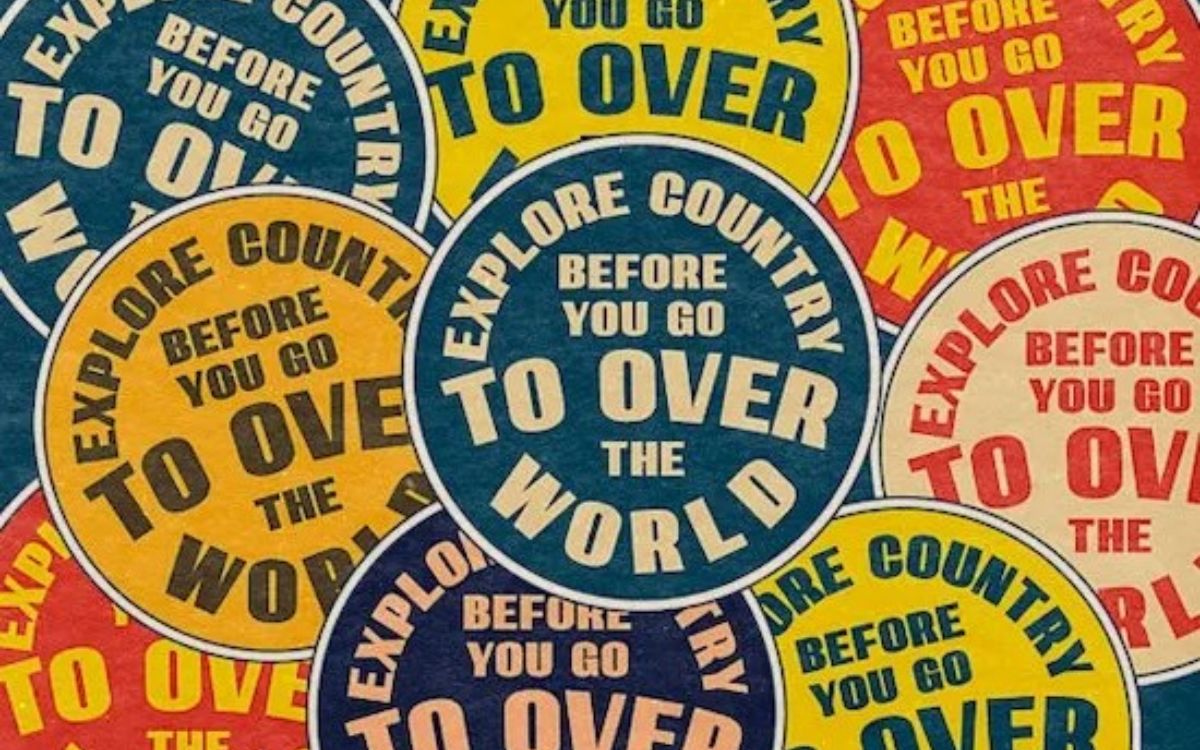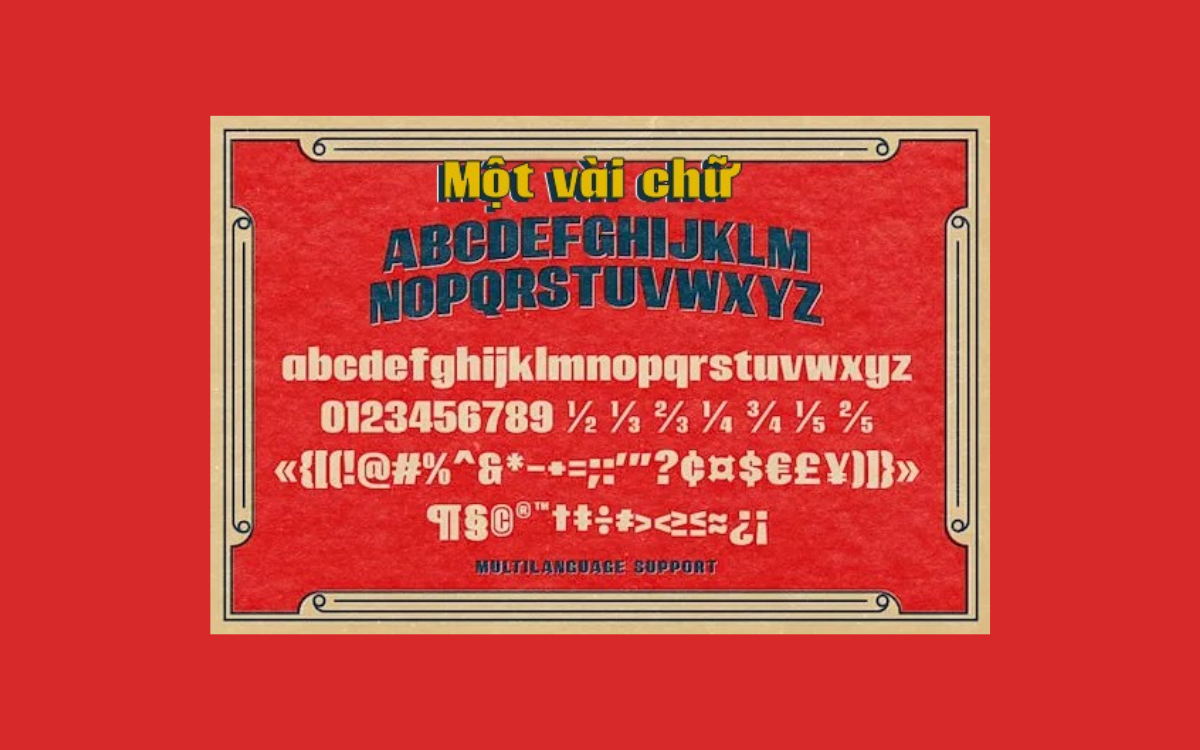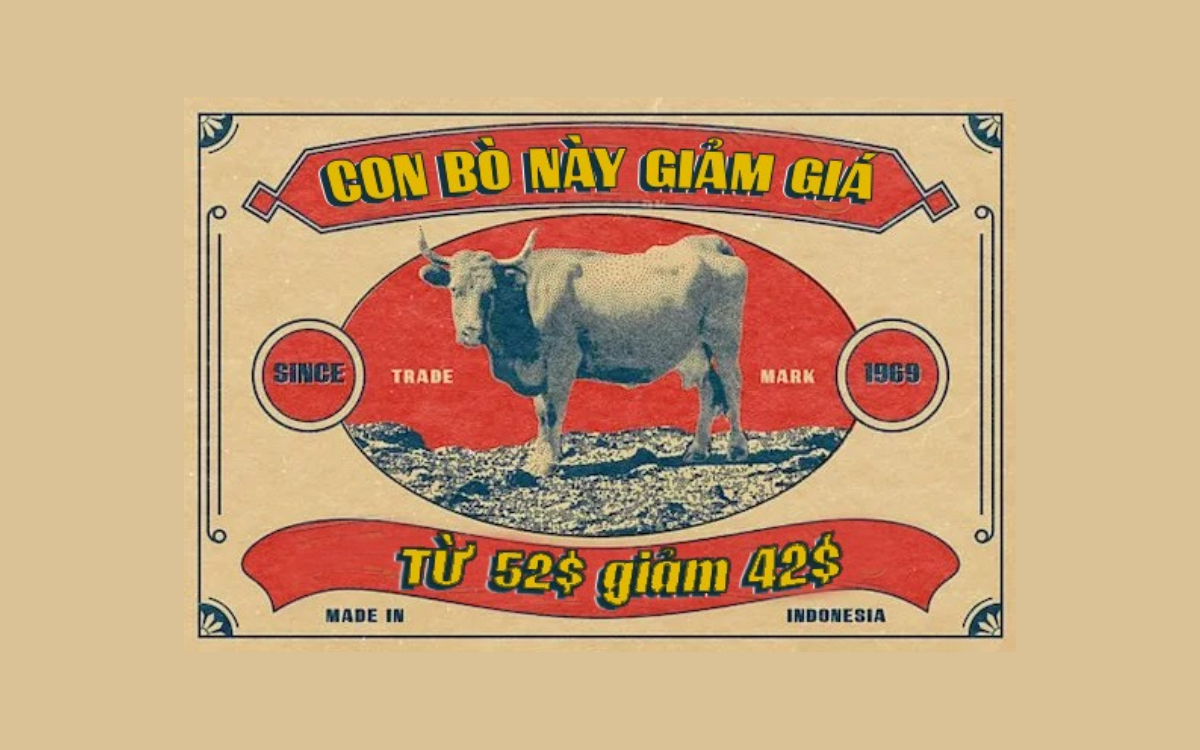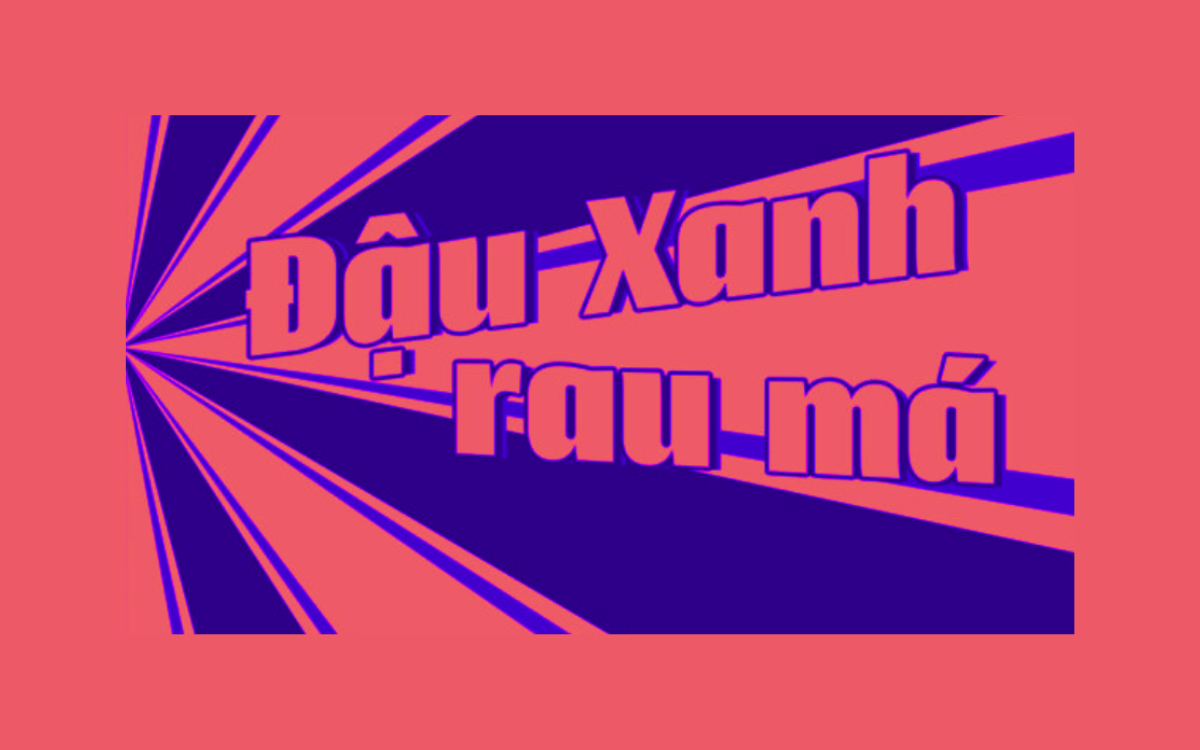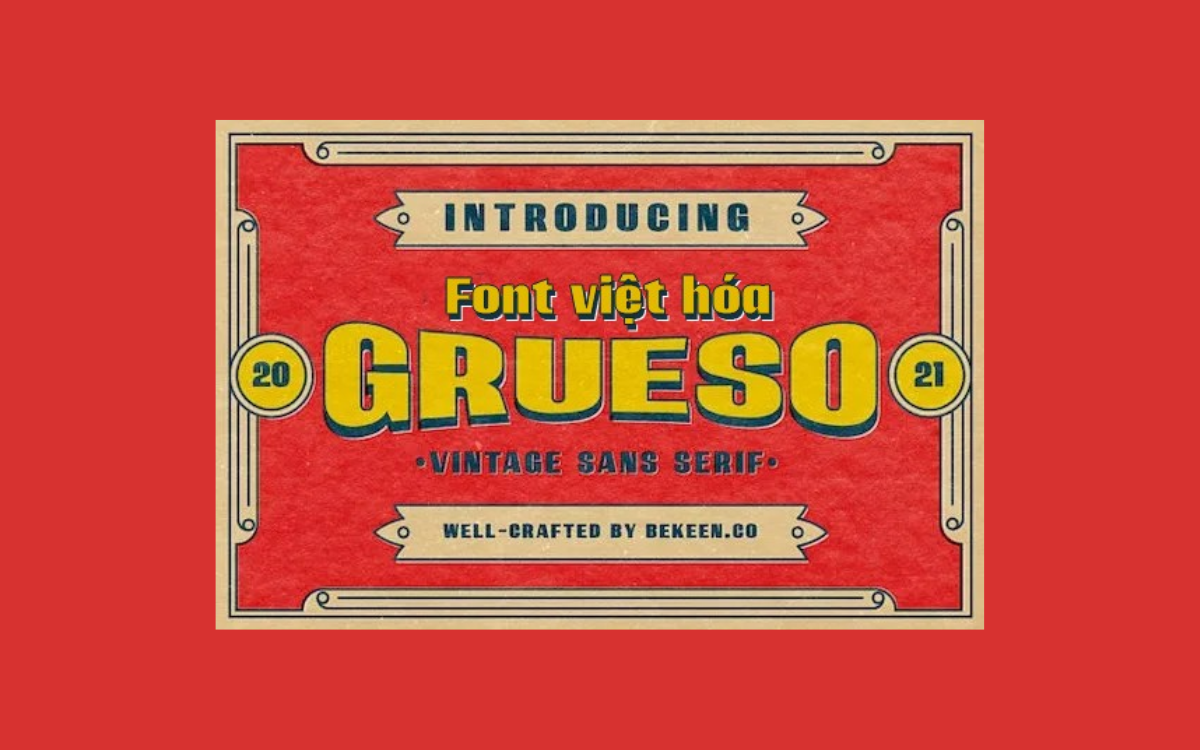
Font MJ Grueso
Tác giả: Måns Grebäck
Ngày phát hành: 2018
Ngôn ngữ: Tiếng Việt, Tiếng Anh
Bộ Font: Font MJ Grueso
Phân loại: Đậm nét
Kiểu chữ: Display
Độ dày: Regular
Font MJ Grueso là một phông chữ sans-serif đậm nét, mang lại cảm giác mạnh mẽ và hiện đại. Với các đường nét dày và chắc chắn, Grueso đặc biệt phù hợp cho các thiết kế cần sự nổi bật, như tiêu đề, biểu ngữ, hay poster. Phông chữ này thuộc bộ font chữ không chân, không chỉ tạo ấn tượng thị giác mạnh mẽ mà còn giúp truyền tải thông điệp một cách rõ ràng và trực quan. Font MJ Grueso là sự lựa chọn lý tưởng khi bạn muốn nhấn mạnh nội dung và tạo sự thu hút ngay từ cái nhìn đầu tiên.